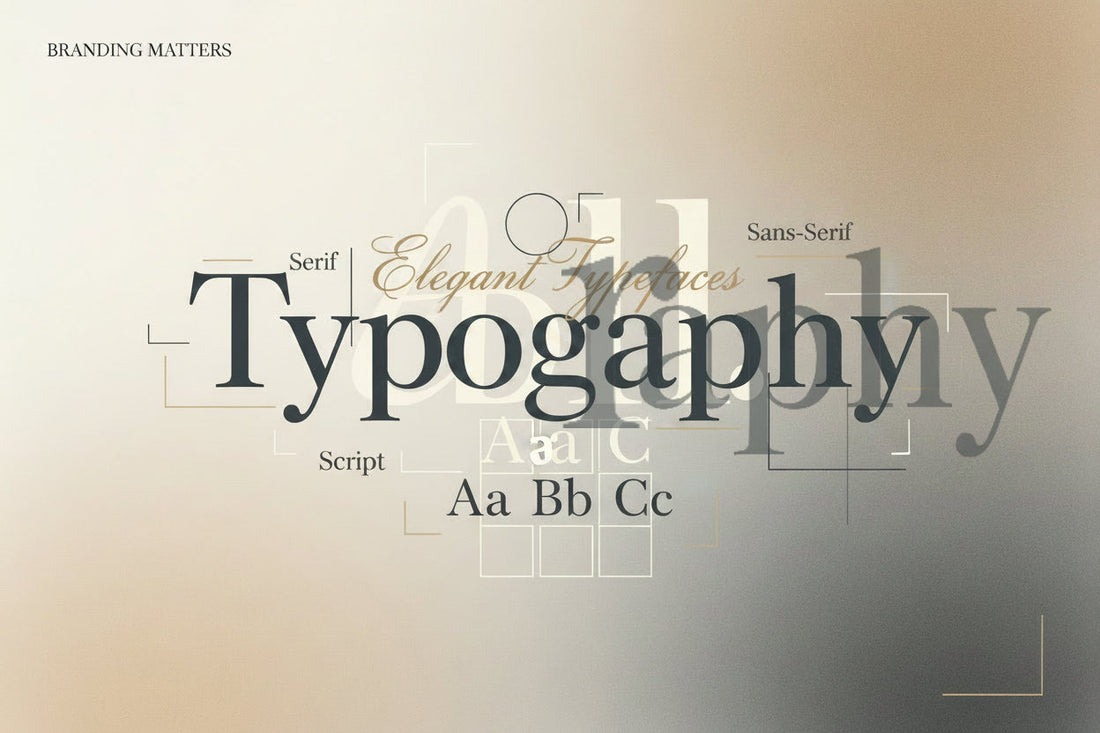
Cómo Elegir la Tipografía Perfecta para tu Marca
La tipografía es la voz visual de tu marca
Antes de que alguien lea una sola palabra de tu contenido, la tipografía ya comunicó algo. Elegante o casual, moderno o clásico, serio o juguetón — cada fuente transmite una personalidad. Elegir bien puede elevar tu marca; elegir mal puede sabotearla.
Los 5 tipos de fuentes y qué comunican
1. Serif — Tradición y autoridad
Fuentes como Times New Roman, Garamond y Georgia tienen pequeños remates en los extremos de las letras. Comunican tradición, confianza y autoridad. Ideales para marcas de lujo, editoriales, firmas legales y finanzas.
Ejemplos de marca: Vogue, The New York Times, Tiffany & Co.
2. Sans-Serif — Modernidad y claridad
Sin remates, limpias y directas. Helvetica, Futura y Montserrat son las favoritas del diseño contemporáneo. Comunican modernidad, accesibilidad y claridad. Perfectas para tecnología, startups y marcas minimalistas.
Ejemplos de marca: Apple, Google, Airbnb, Spotify.
3. Script / Manuscrita — Creatividad y personalidad
Imitan la escritura a mano. Comunican calidez, creatividad y exclusividad artesanal. Funcionan bien como fuentes de acento o en logos, pero son difíciles de leer en textos largos.
Ejemplos de marca: Coca-Cola, Instagram (logo original), Cadillac.
4. Display / Decorativa — Impacto y originalidad
Diseñadas para destacar en tamaños grandes. Cada una tiene una personalidad única y fuerte. Ideales para titulares, logos y piezas de marketing, nunca para cuerpo de texto.
5. Monospace — Tecnología y precisión
Cada carácter ocupa el mismo ancho. Asociadas con código, tecnología y precisión. Courier, Roboto Mono y Space Mono son ejemplos populares.
El sistema tipográfico de 2-3 fuentes
Las marcas profesionales rara vez usan más de 3 fuentes. El sistema clásico es:
- Fuente principal (Display/Heading): Para títulos y elementos de alto impacto. Puede ser más expresiva.
- Fuente secundaria (Body): Para textos largos. Debe ser altamente legible. Generalmente una sans-serif o serif simple.
- Fuente de acento (opcional): Para detalles, citas o elementos decorativos. Puede ser una script o display.
Combinaciones tipográficas que funcionan
Estas parejas son probadas y funcionan en branding profesional:
- Playfair Display + Lato — Elegante y legible. Ideal para marcas premium.
- Montserrat + Merriweather — Moderno con profundidad editorial.
- Raleway + Open Sans — Limpio y contemporáneo para startups.
- Cormorant Garamond + Jost — Lujo minimalista, perfecto para moda y lifestyle.
Reglas de oro para usar tipografía en tu marca
- Jerarquía visual: Tamaños diferentes para títulos, subtítulos y cuerpo. El lector necesita saber dónde mirar primero.
- Contraste: Combiná fuentes con personalidades distintas (ej: serif + sans-serif). Dos fuentes similares generan confusión.
- Consistencia: Usá las mismas fuentes en todos tus canales: web, redes, materiales impresos.
- Legibilidad primero: Una fuente hermosa que no se puede leer es un error de branding.
Conclusión